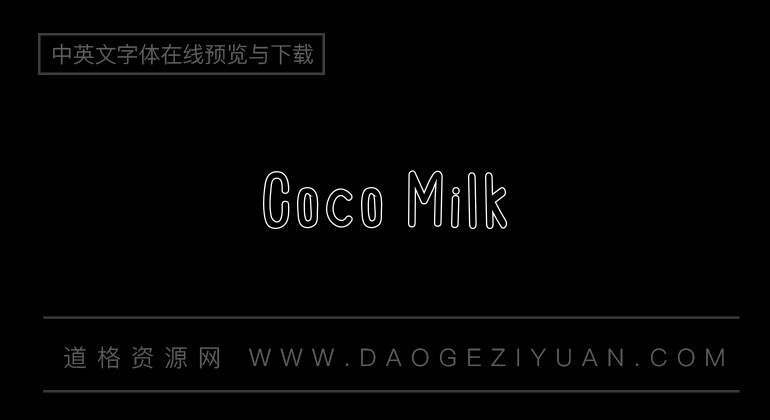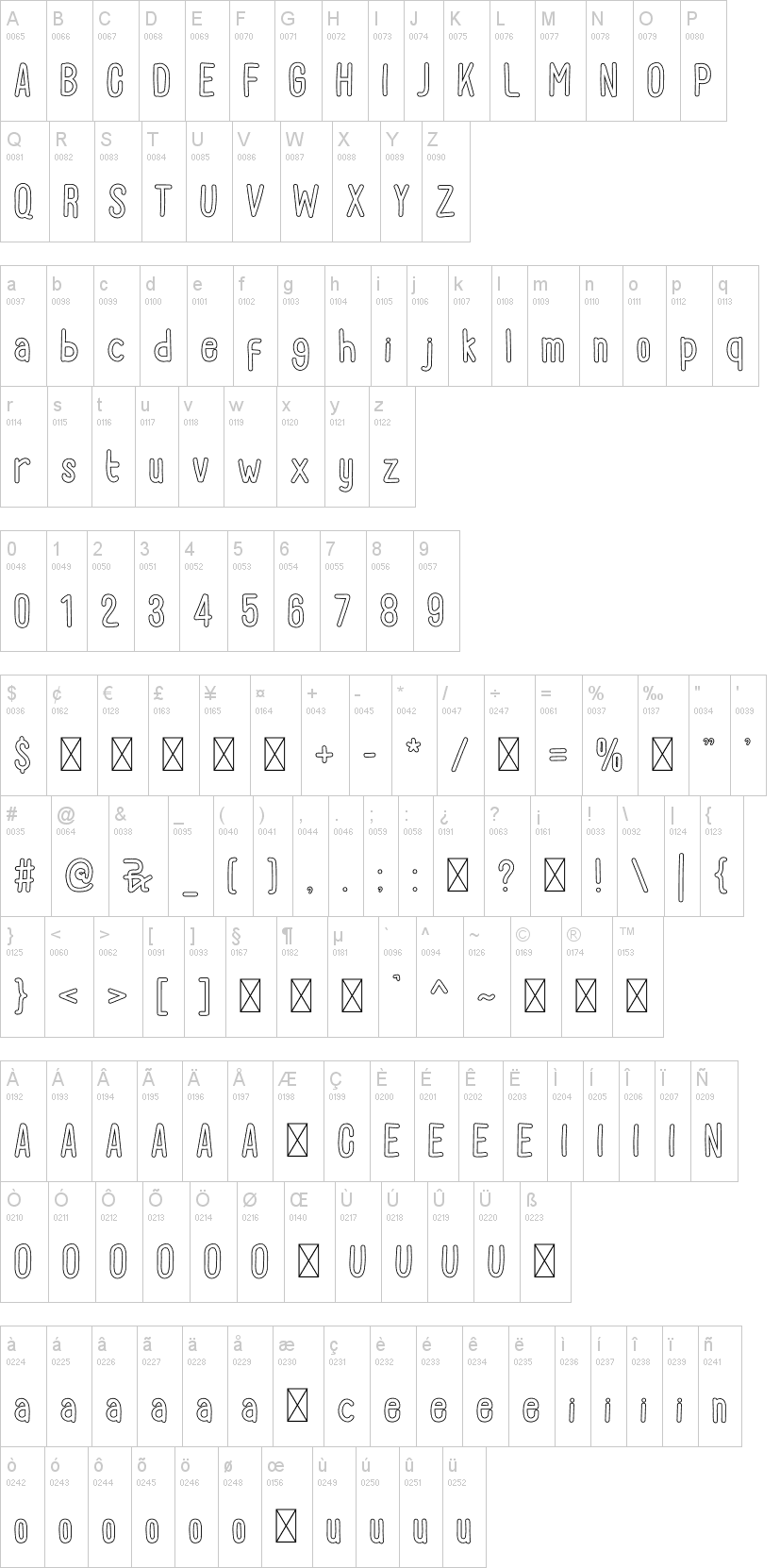
Coco Milk
Coco Milk 字体是一款可爱的欧文字体,它由美国设计师 Laura Worthington 创作。Coco Milk 字体的特点是细节丰富,字形轻快,拥有温柔的曲线,让人看起来更加可爱。它的字体结构紧凑,拥有大量的英文字母、数字和标点符号,可以用于制作各种类型的文字,包括卡片、邀请函、海报等。Coco Milk 字体的名字源自它的设计师,Laura Worthington,因为她喜欢喝可可牛奶。
Coco Milk是一款非常不错的手写艺术字体,具有很好的视觉感,适合于文化类的宣传设计、商业类品牌的广告和产品包装设计以及个性化文字排版等较多场景。